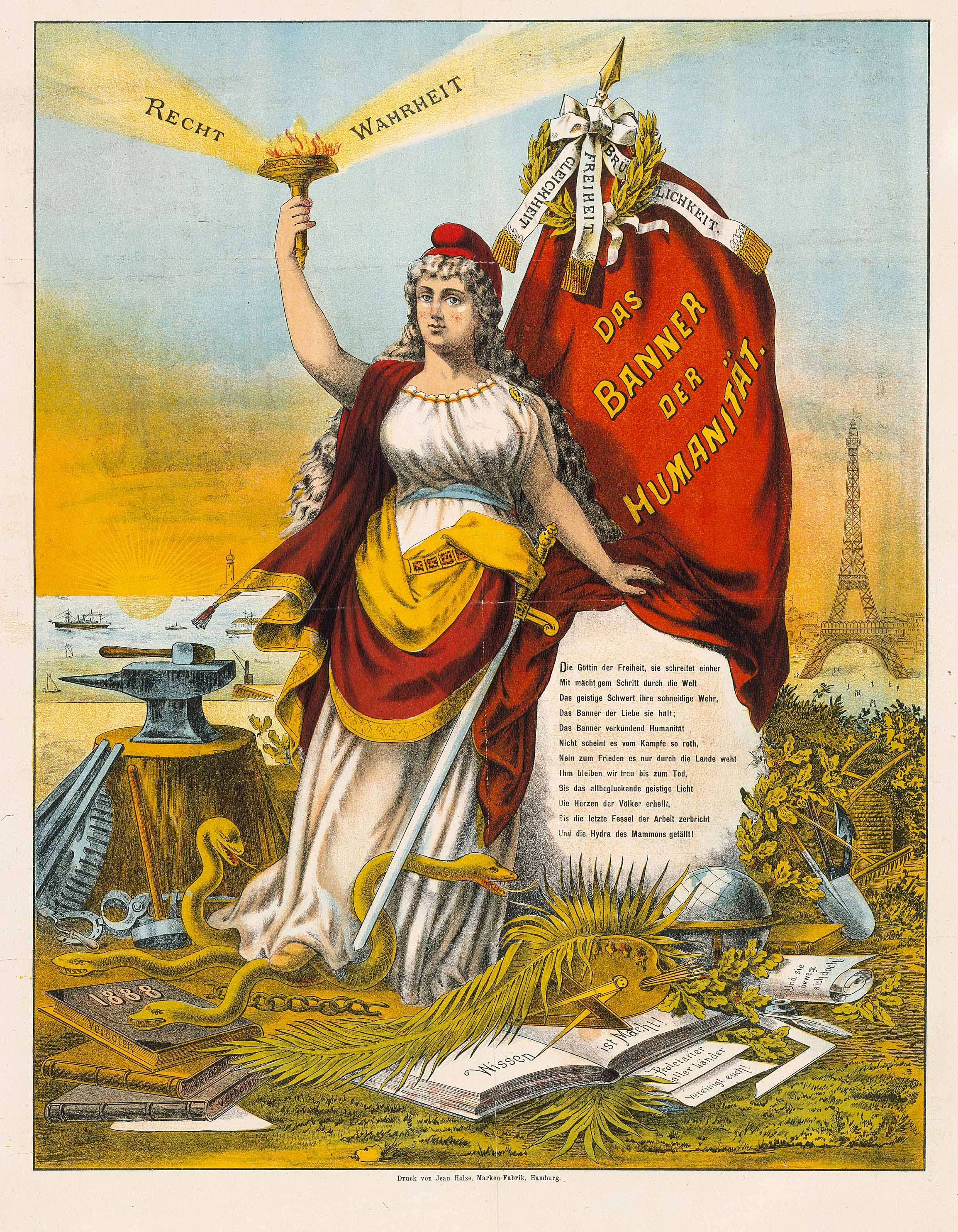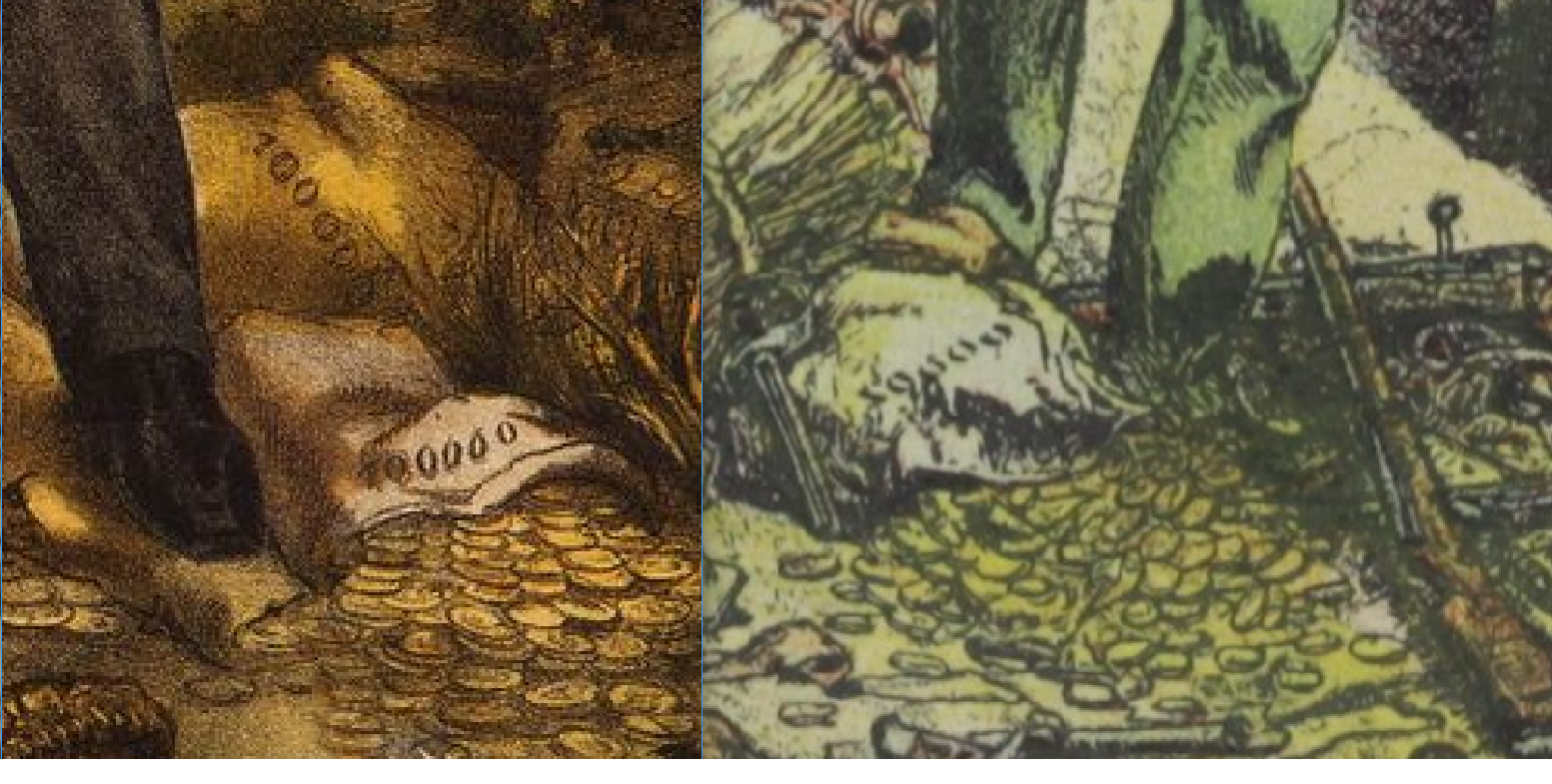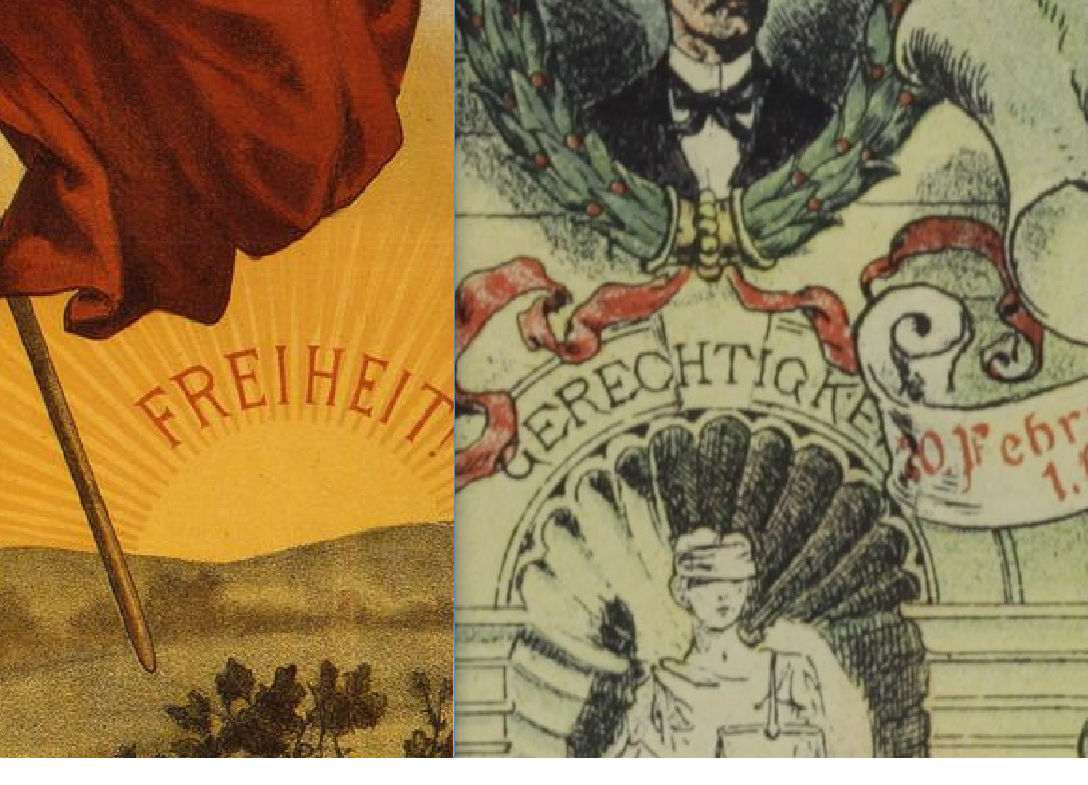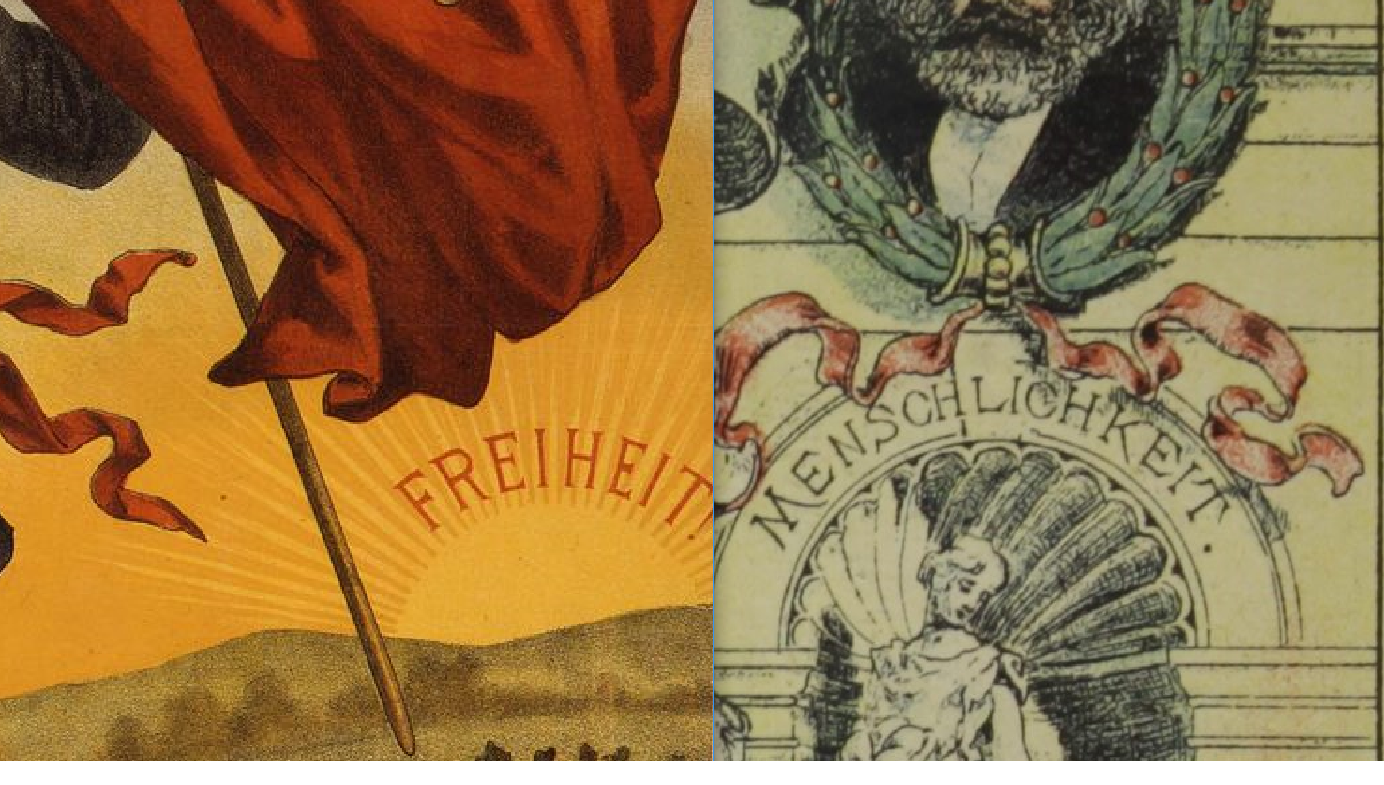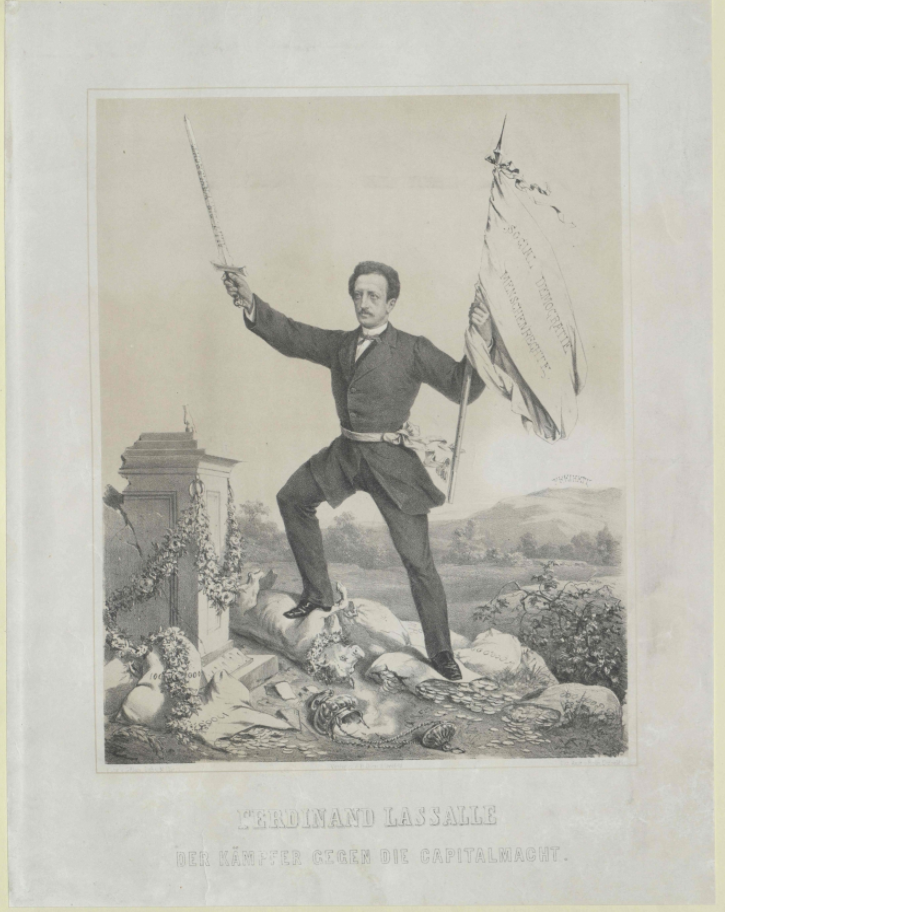
Ferdinand Lassalle Bild
ich habe eine Frage,  kann es derselbe Künstler sein?
Ich denke das Bild ist von Friedrich Kaskeline 1892.
Ein paar Studenten und junge Akademiker schlossen sich zu einem Verein zusammen, der sich unschuldig als "Lese- und Diskutierklub Veritas" gab. Mit dabei waren etwa der spätere Abgeordnete zum Nationalrat Karl Leuthner, der Illustrator der "Glühlichter", Fritz Kaskeline, der Schriftsteller Willy Handl oder der spätere Verfasser der fünfbändigen "Geschichte der österreichischen Sozialdemokratie", Ludwig Brügel.
Gedenkblatt 1890
Werbung für Gedenkblatt 1890
Ich habe auch 2 Bilder gefunden die gut zu der Werbung passen würden.
Ich vermute, 1892 hat Kaskeline das Alte verbotene Bild aus dem Jahr 1872( Borne Verlag 1872) neu gezeichnet. http://anno.onb.ac.at/cgi-content/anno?aid=wrz&datum=18720716&seite=15&zoom=33&query="Kämpfer_gegen_die"%2B"Capitalmacht"&ref=anno-search
Die erste Version hat eine andere Schriftform und SoCial DemoCratie, in der 2ten Pracht-Version ist das K dann betont. Leider habe ich schon 4MB hochgeladen ich hätte noch Hinweise.
Ab 1893 (nach Kaskeline Bild1891/92) gibt es wieder Polizeiberichte über Beschlagnahme, der Verlag der Bilder war dann Hans Stolze in Hamburg.
Wieder ein Indiz, Das Bild https://www.leo-bw.de/themen/landesgeschichte/wurttemberg-im-19./20.jahrhundert/wurttemberg-im-bismarckreich über dem Ambos ist wieder die Sonne zur Freiheit, auf diesem Bild von Fritz Kaskeline ist der Verlag angegeben, Jean Stolze Hamburg. Leider wurde der Link zu dem Brief, Fritz Kaskeline an Friedrich Engels gelöscht, jetzt mache ich mir die Mühe nicht noch einen link anzugeben, Victor Adler an Friedrich Engels, Adler bekam 500 Mark von Deutschen Verlagen, in Österreich war das nicht so einfach.
Ich steh gerade auf der Leitung: Welches ist genau das Bild, bei dem Du Kaskeline als Urheber vermutest? Ich sehe nur die verschiedenen Ausschnitte bei Deinem ersten Post …
Er war einer von euch!